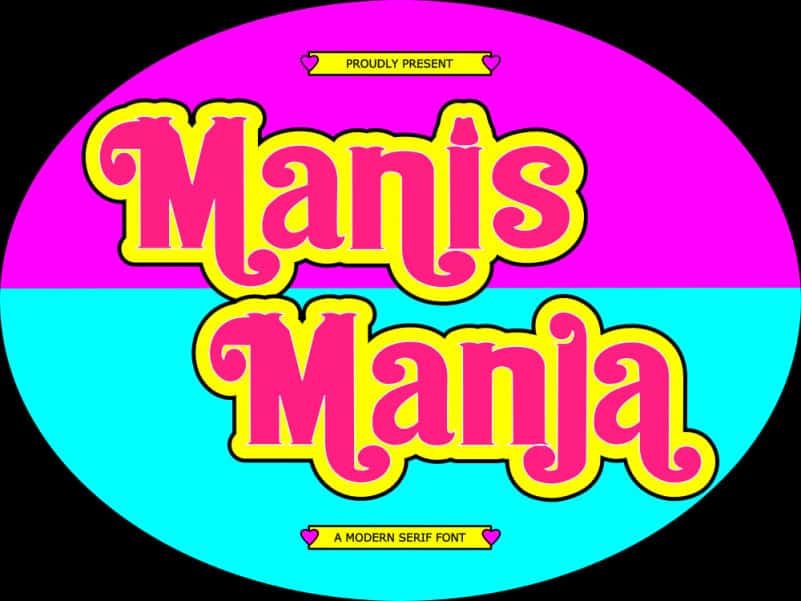
Manis Manja Serif Font
Manis Manja adalah font serif modern. Ini dapat dengan mudah dicocokkan dengan memenuhi proyek yang sangat besar, jadi tambahkan itu ke ide kreatif Anda dan memantau bagaimana itu membuatnya menonjol!